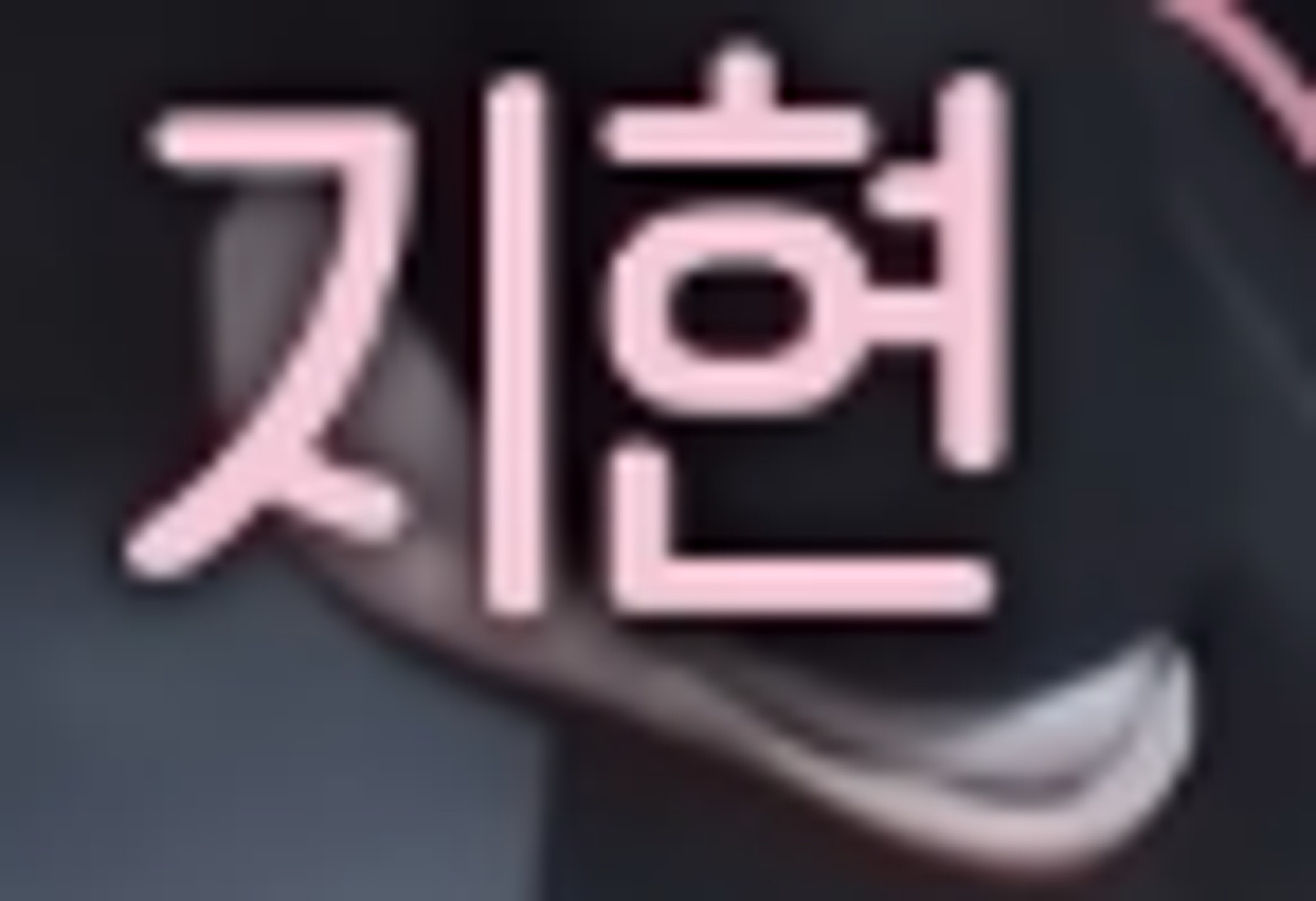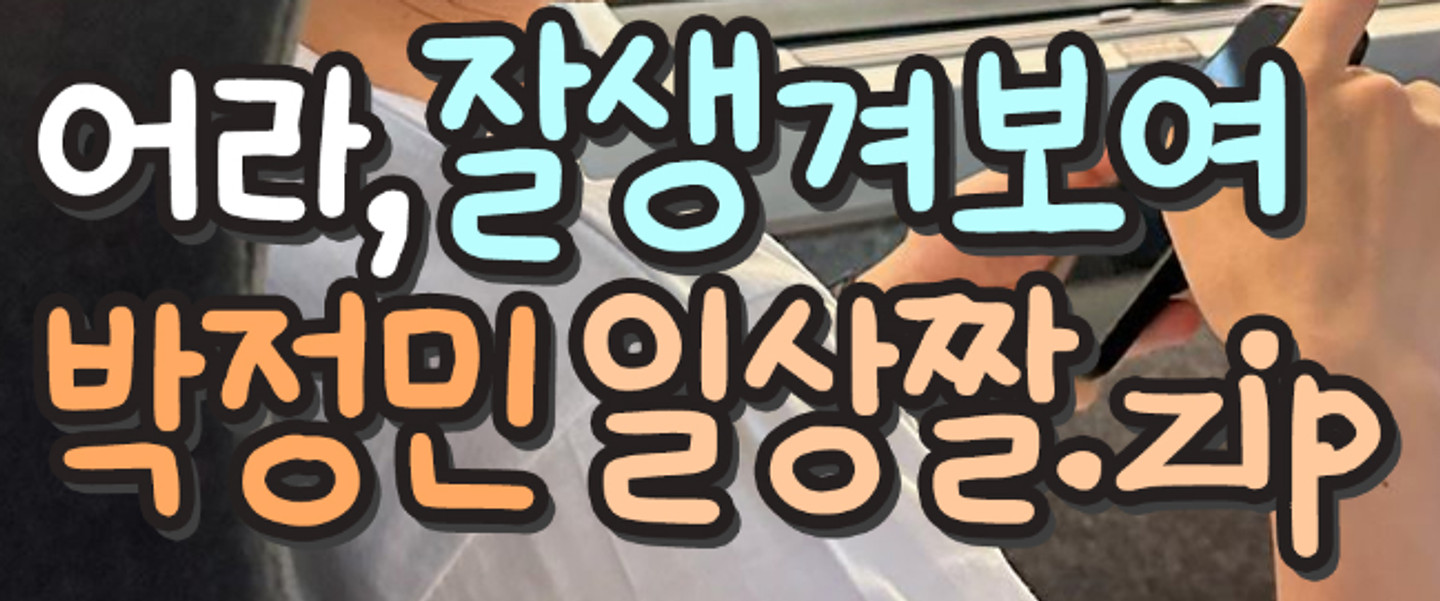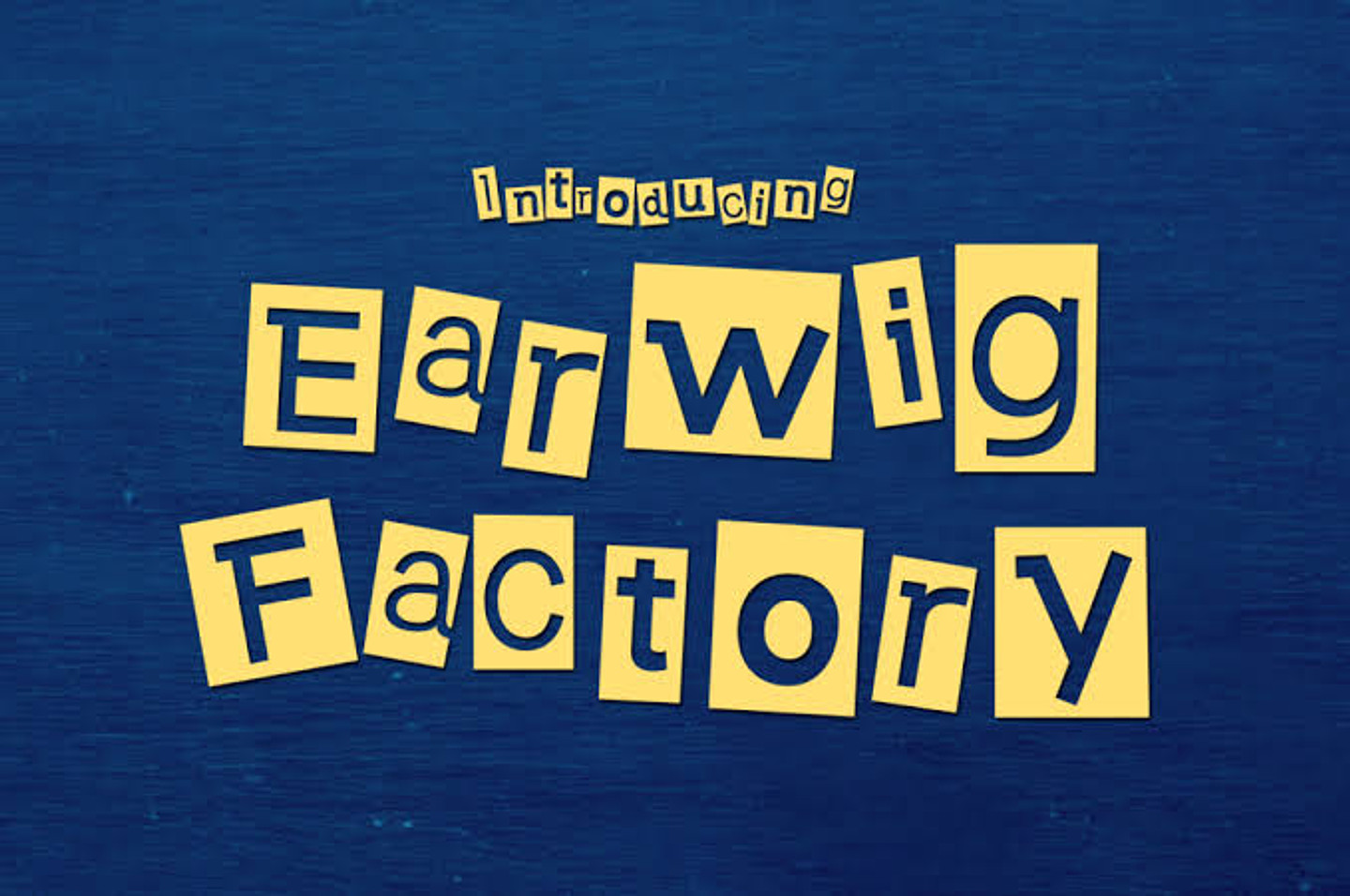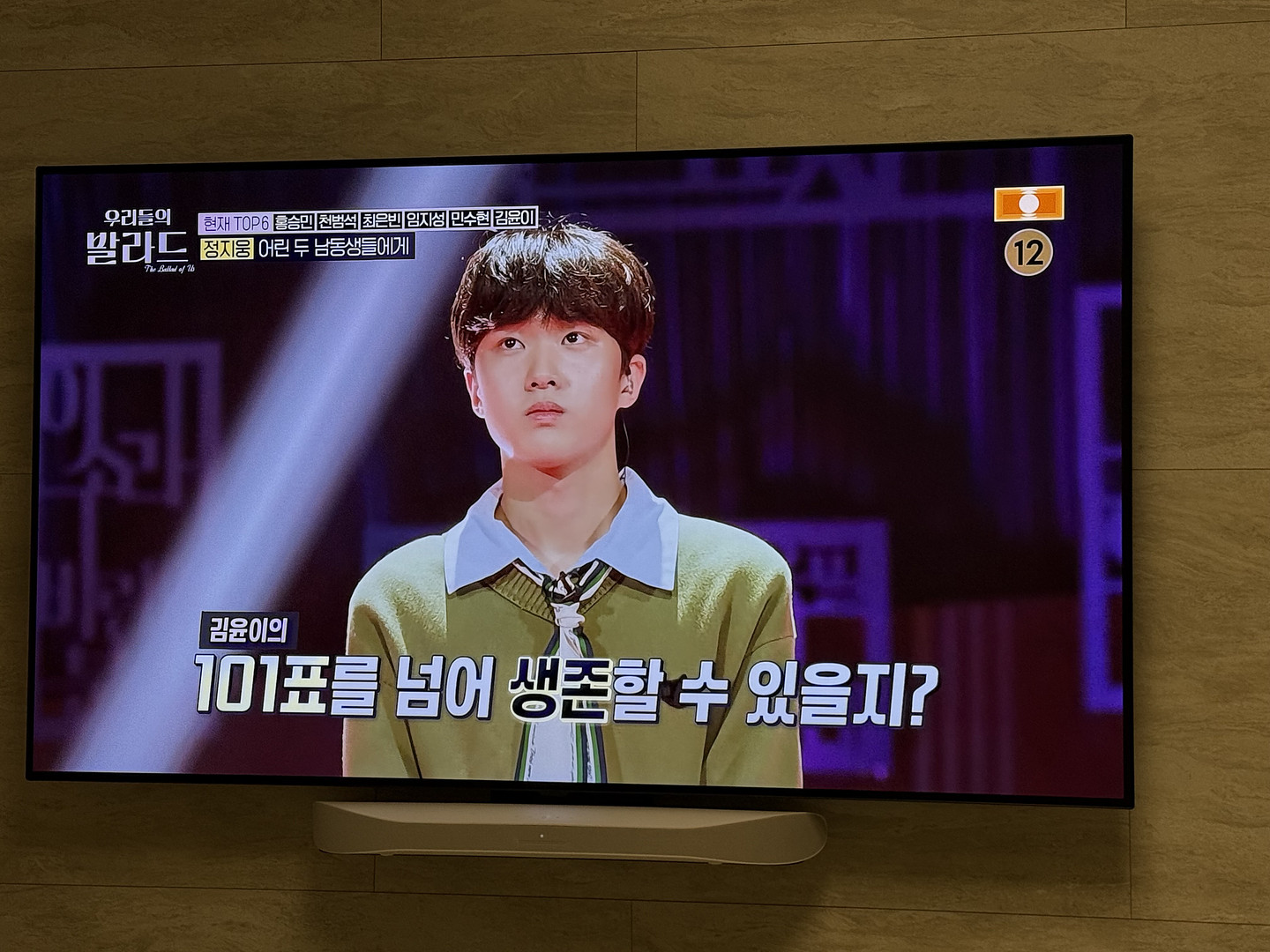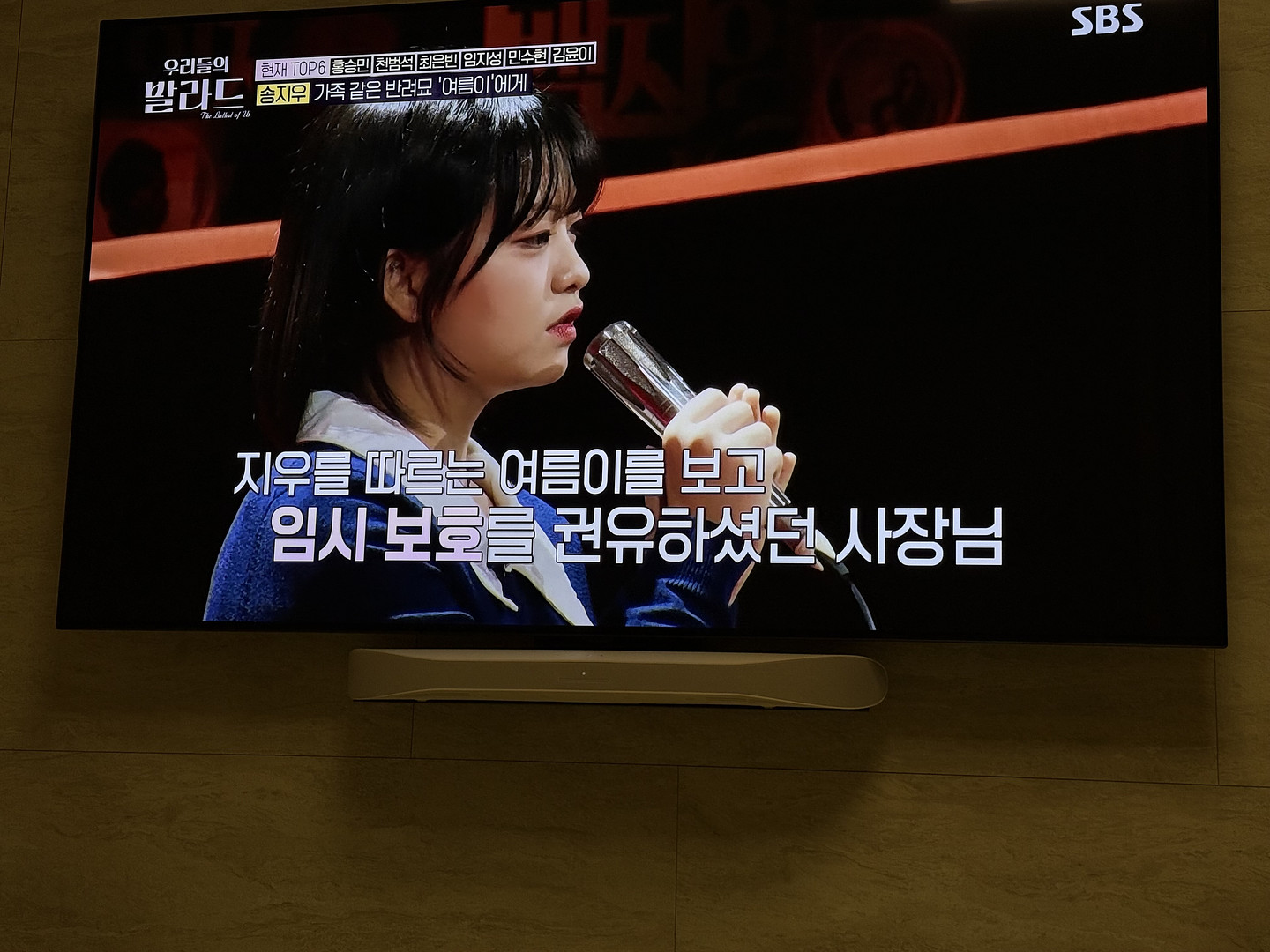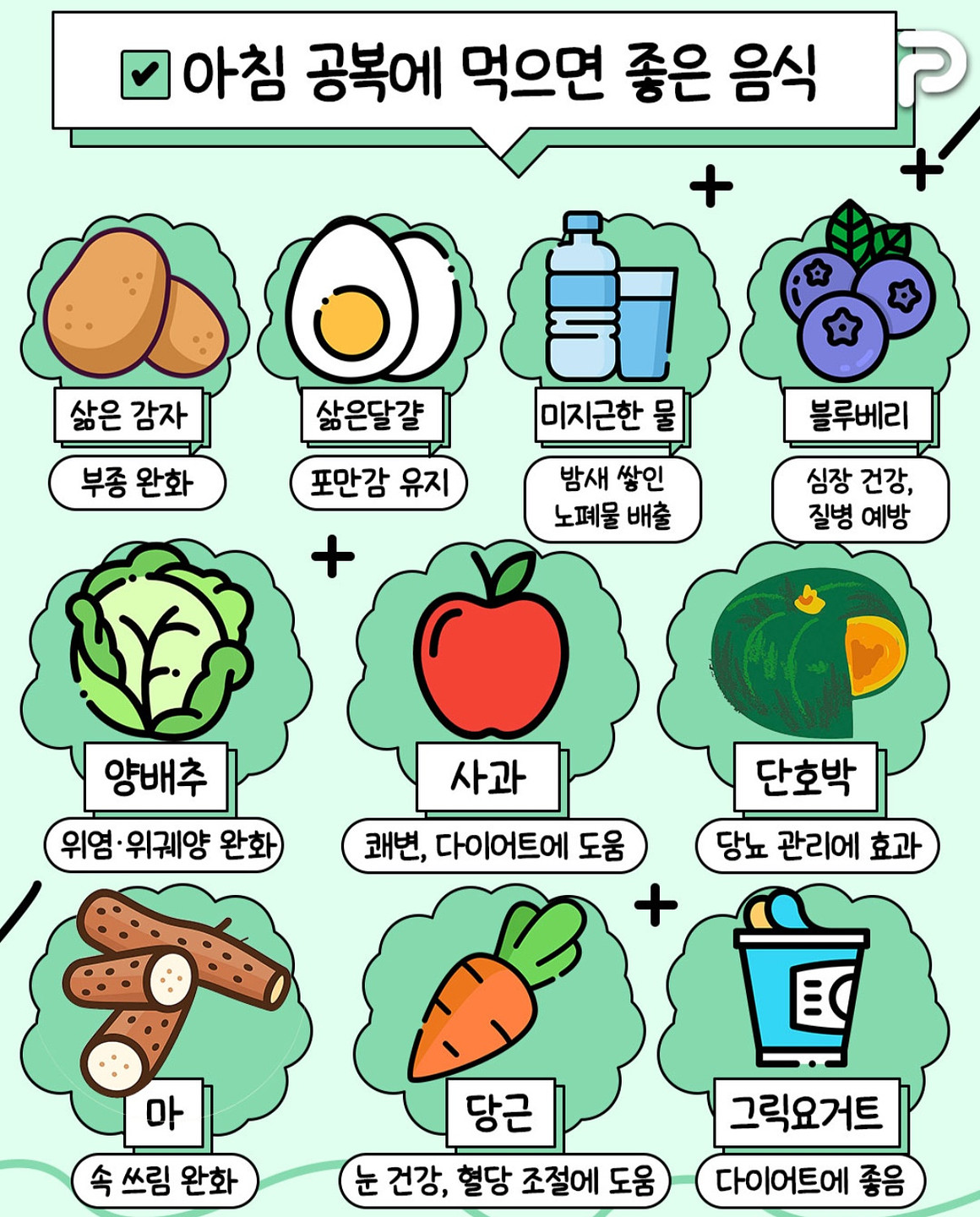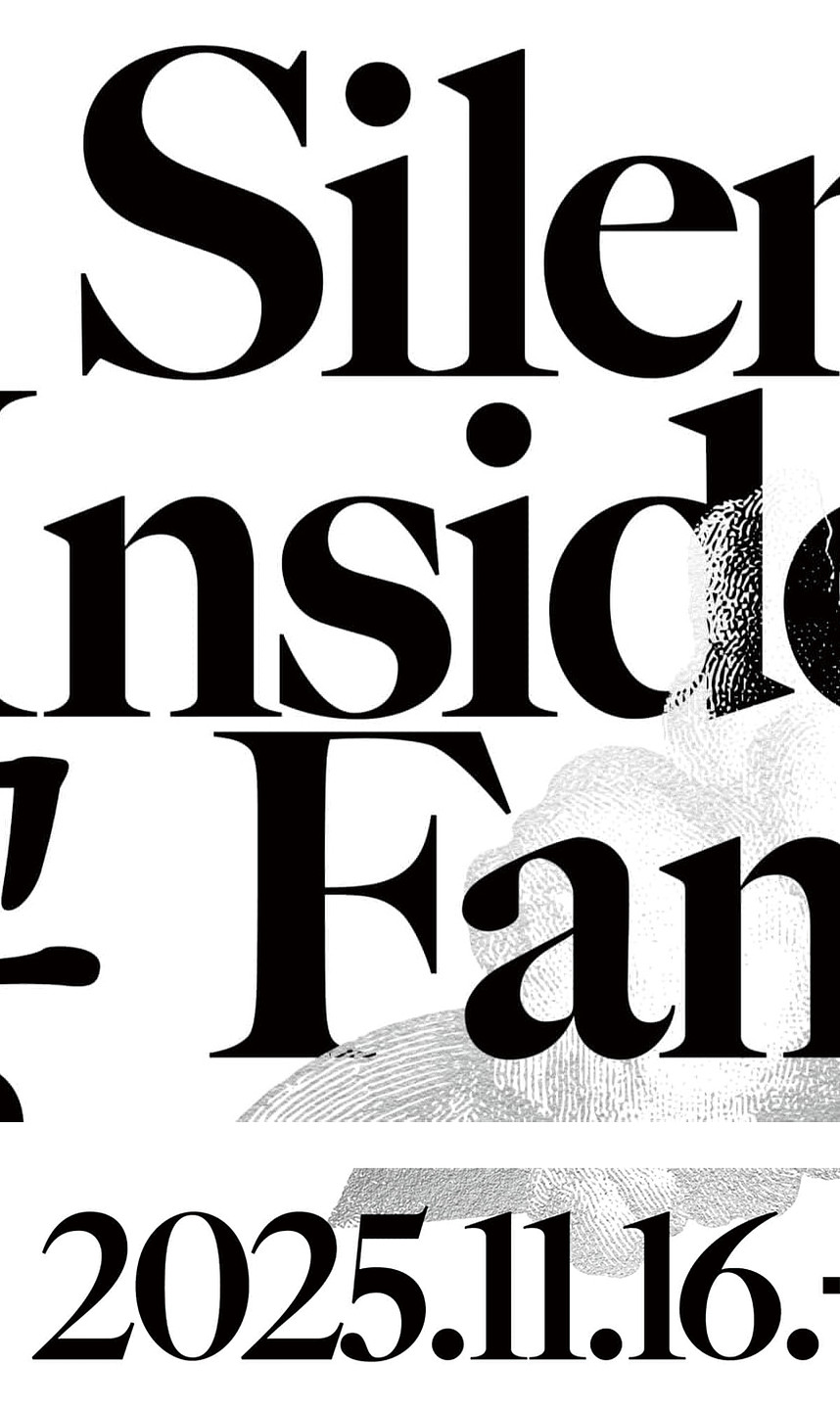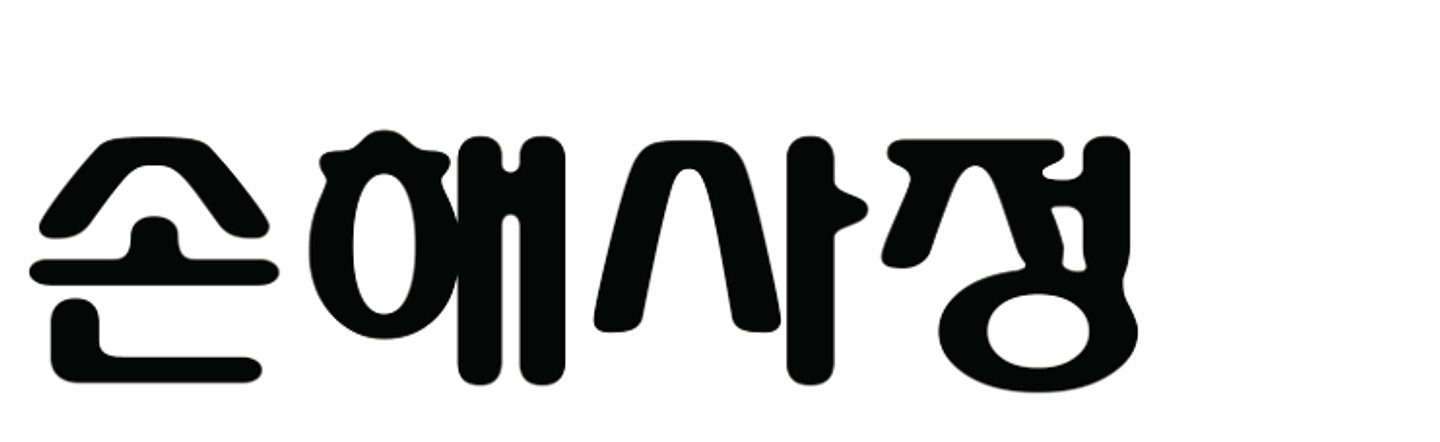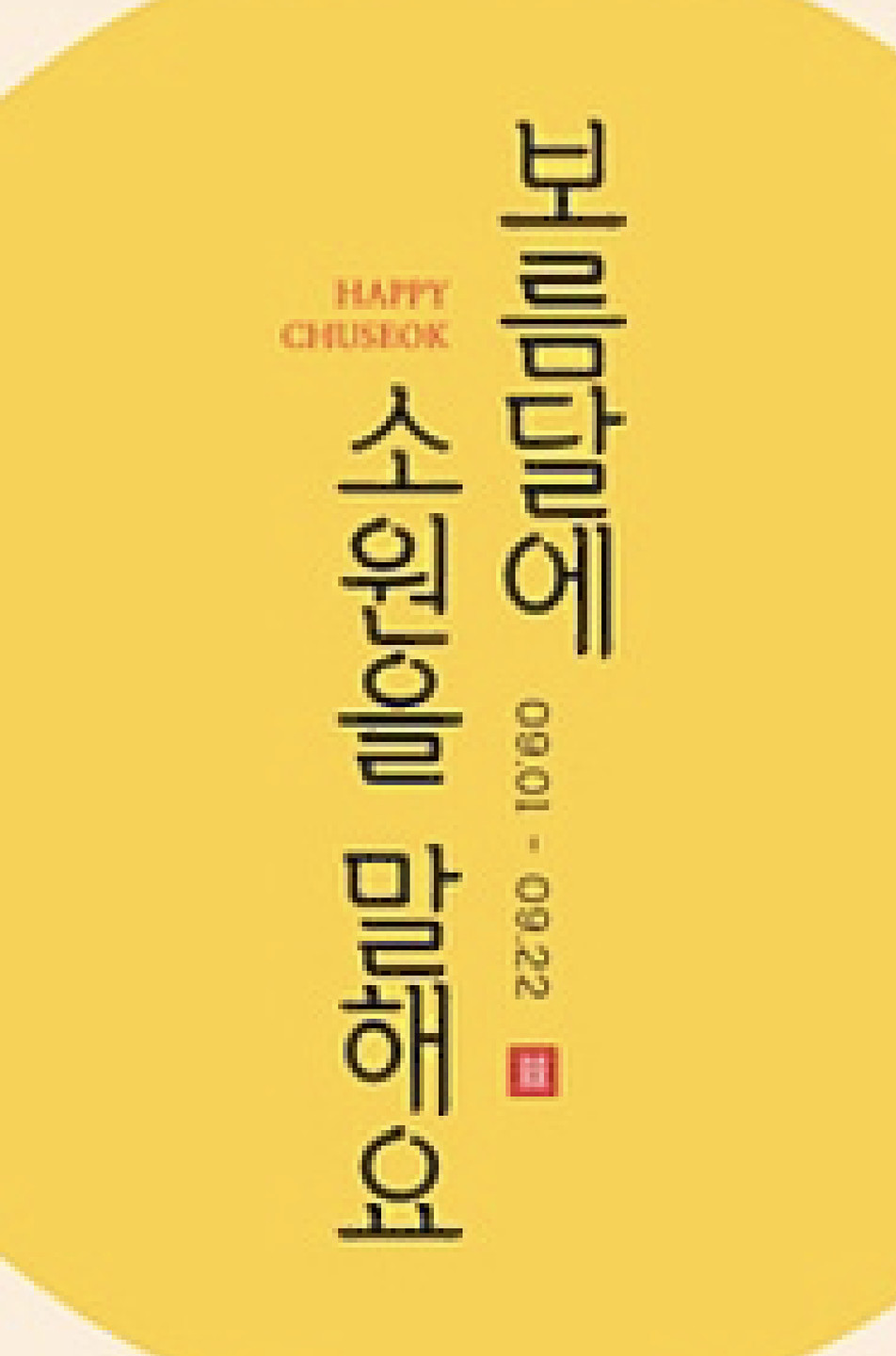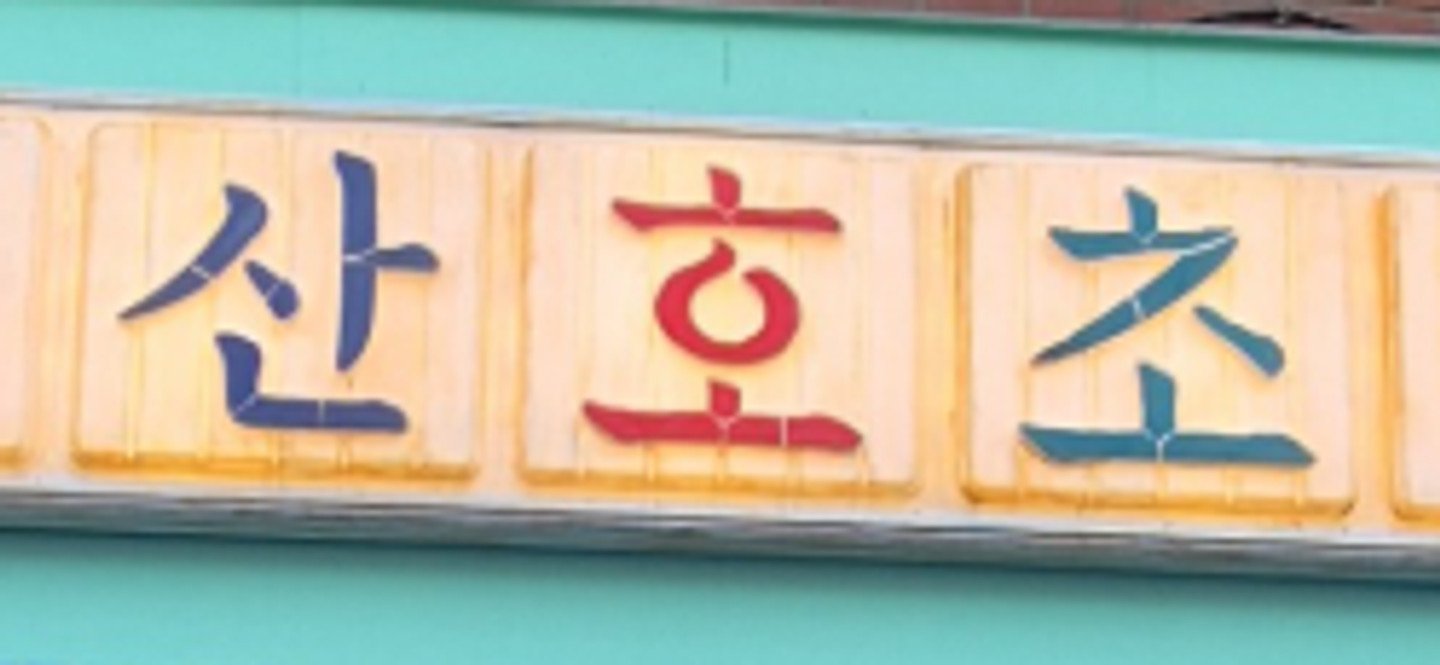
폰트 이름 궁금해요!
ㄱ무슨 글씨체일까요
이거무슨폰트인가여
설화수 영문폰트 궁금합니다. 인스타그램에 쓰는 폰트요
쇼츠 자막인데 무슨 폰트일까용??
태도에 관하여 - 임경선 책인데요 이 폰트는 뭐인지 알 수 있을까요?!
메뉴에 사용된 폰트를 알고 싶어요 어떤분은 a고운글씨M 이라고 하시는데... 폰트 모양이 조금 다른거같아 문의 드립니다
현대산업차량 홈페이지에서 캡쳐했고 산돌에서 찾아도 안나와서 물어봅니다 어떤폰트일까요?
폰트 이름 궁금!!
무슨 폰트인지 궁금해요. 이미지로 폰트 검색해도 안 나오네요ㅠ 아시는 분 알려주시면 감사하겠습니다..!
폰트 알려주세요~
교과서에 있는 폰트입니다
혹시 무슨 폰투인지 알 수 있을까요?
이거 무슨 폰튼가용???
요거 무슨 폰트일까용??
요거 무슨 폰트 일까유???
ㅇ이랑 ㅎ이 살짝 틀어져있고 ㅅ의 뻗침이 없는게 너무 예뻐서 어떤 폰트인지 궁금하네요 ㅠㅠ
이 폰트 뭘까유ㅠ
이거 뭔가요?
폰트 이름 궁금해요!! 혹시 아시는 분 계실까요!!
요즘 인스타 릴스에 자주 보이는 폰트인데 이름이 뭔지 모르겠어요…ㅠㅠ 혹시 아시는 분 계실까용??
SK나이츠 한글 마킹 폰트인데, 어떤 폰트인지 아시는 분 계신가요? 일단 산돌구름에 검색했을때는 똑같은 폰트는 안 나오는 것 같네요..
이거 무슨 폰트인지 아시는분 계실까요??ㅠㅠ
스캔한 폰트라 약간 깨져보이는데.. 어떤 폰트인지 정말 궁금합니다..!!
이거 무슨 폰트에요?ㅠㅠ
폰트 뭔지 궁금해요 ㅎㅎ
네모딱진데 가독성 좋아서 궁금해요
손글씨 느낌나는데 폰트 뭔지 궁금해요!
폰트 알 수 있을까요..? ㅠ
이 서체가 뭔가요?
무슨폰트인지 알려주세요
해당 폰트 아시는 분 계실까요 ㅠㅠ
크게 제대로! 이 폰트 뭘까요?
이 폰트 아시는 분,... ? 알듯 말듯 애매하네요
한글 폰트명 알려주세요~!
2002폰트랑 비슷한데 'ㅁ' 아래 모서리가 둥근 폰트가 찾아지지 않네요 무슨 폰트지 아시는 분 계실까요~?
릴스 썸네일에서 본 폰트인데 정보가 너무 궁금하네요..! 아시는 분 계신가요?
사문 교과서 폰트인데 뭔지 궁금해요
무슨폰트일까용
안원잘부 채널에서 쓰는 폰트인데 폰트정보 알려주세요
SONO, 숫자 마킹에 사용된 폰트가 무엇일까요?
무슨 폰트인가요? 브랜드 로고를 사용할 예정인데,,, 까먹었네요
배민체인줄 알았는데.. 아니여서 비슷한체라도 찾고싶은데 쳇지피티에서도 안나오네요 ㅠ
폰트가 뭘까요..?
네이버 웹툰 작가님이 사용하는 글씨체인데, 너무 알고싶습니다
이거 무슨폰트일까요? 비슷한폰트라도 추천 부탁드립니다!
흘러내리는 글자체 무엇인지 알수 있을까요?
전설의수사 자막 무슨 폰트인가요?
빨간 글씨 빼고 남색 글씨체 뭘까요...
혹시 이 폰트 어떤 폰트인지 알 수 있을까요?
위의 폰트 어떤건지 알려주시면 감사드리겠습니다